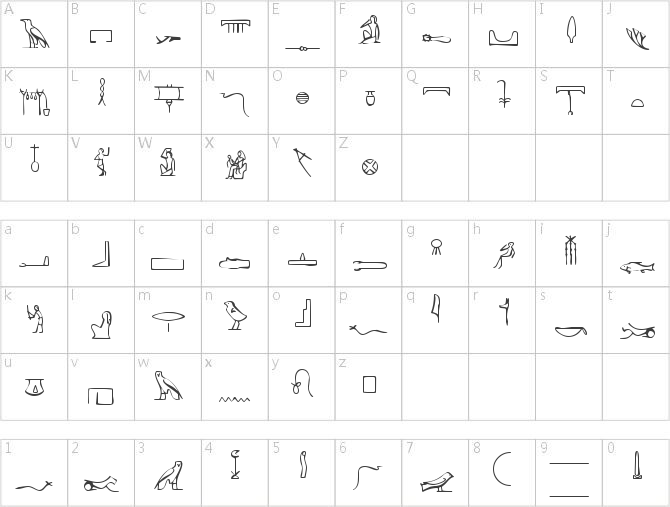
字體名稱: Pharoah
Pharoah Glyph Medium
Pharoah Glyph Medium介紹
Pharoah Glyph Medium字體字庫是一款讓人賞心悅目、百看不厭的英文字體,適合各類廣告和產品包裝設計應用,字體大小0.05MB,格式為ttf字體,上傳用戶是迷路的豬,作者/版權方為未知